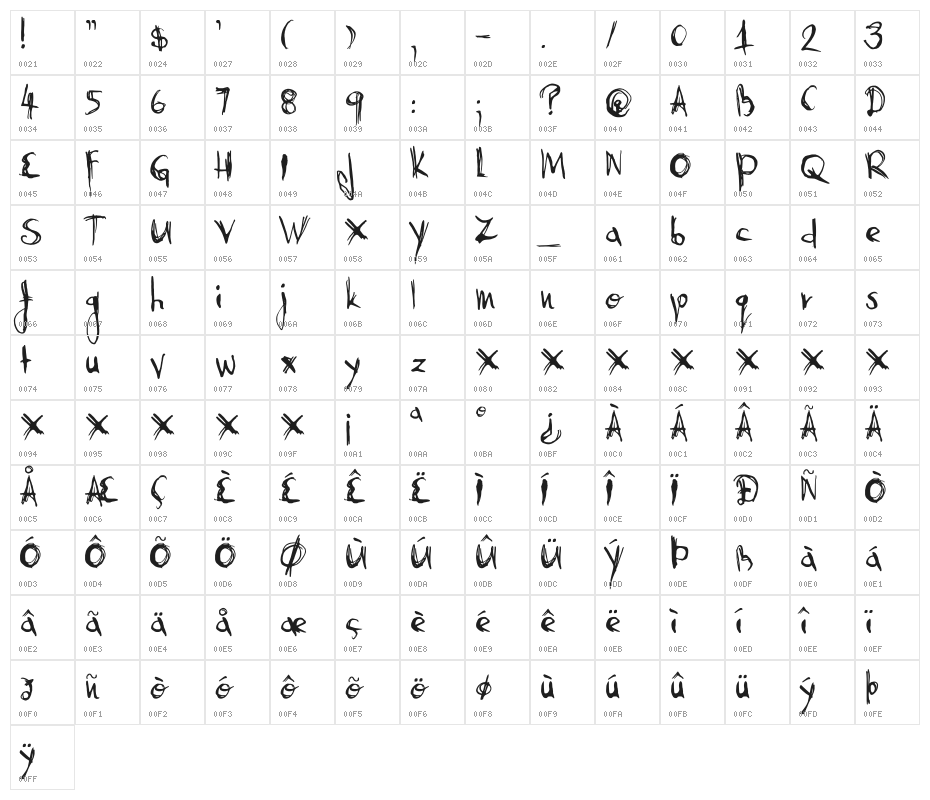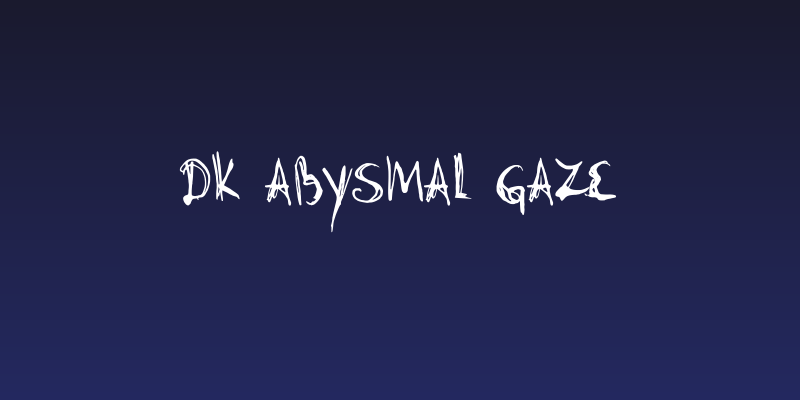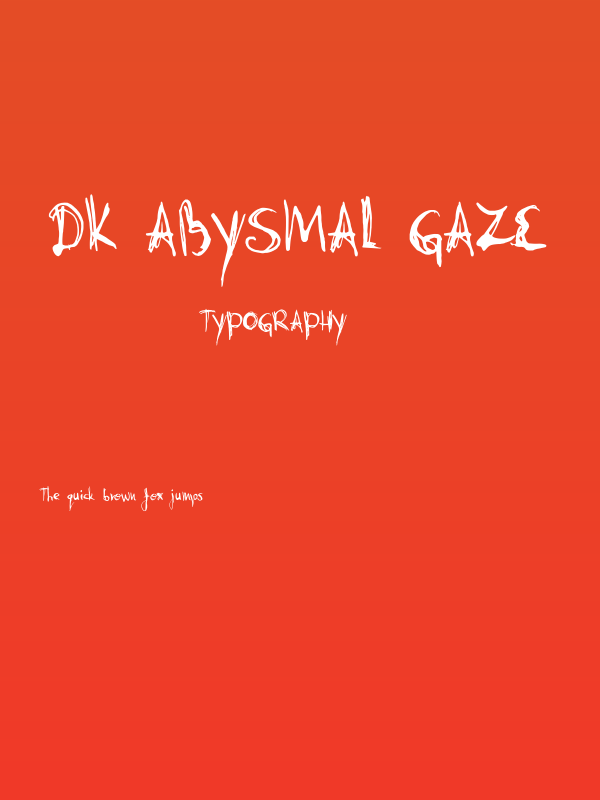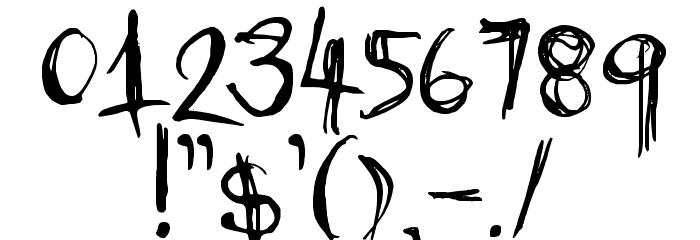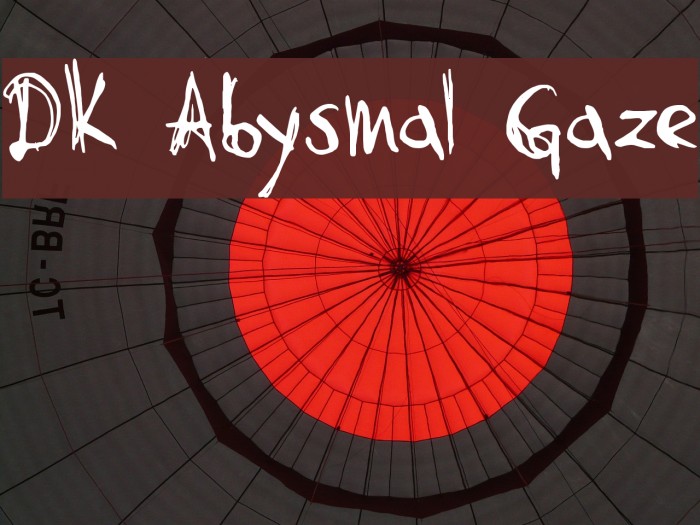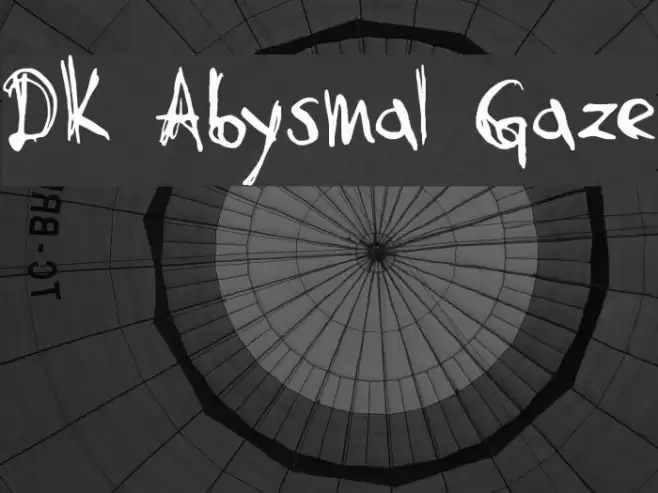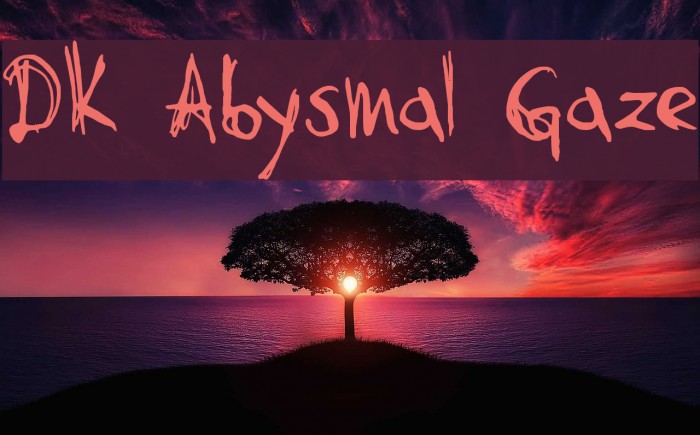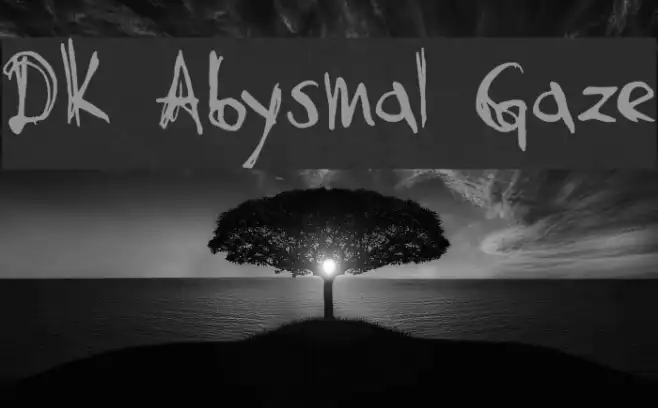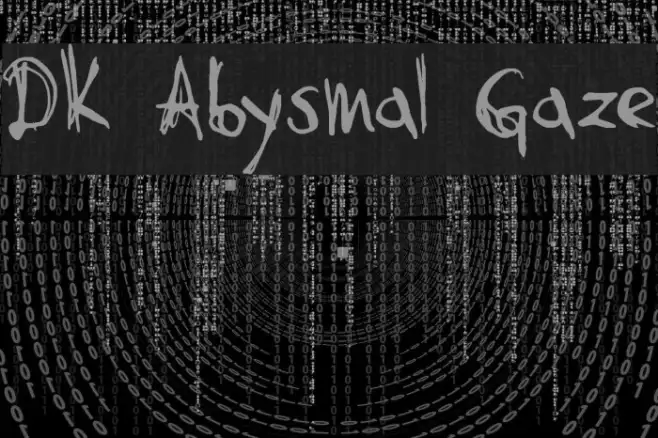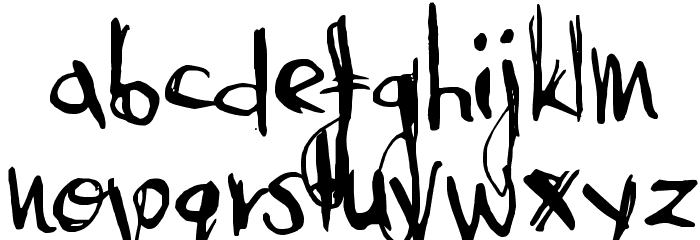
DK Abysmal Gaze Font
| Vorgeschlagene Projekte | Ideal for horror-themed posters, album covers, edgy branding, or any project needing a dramatic and intense visual impact. |